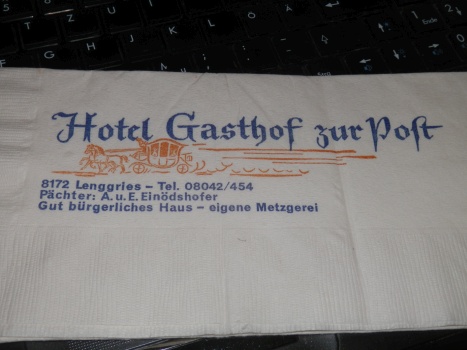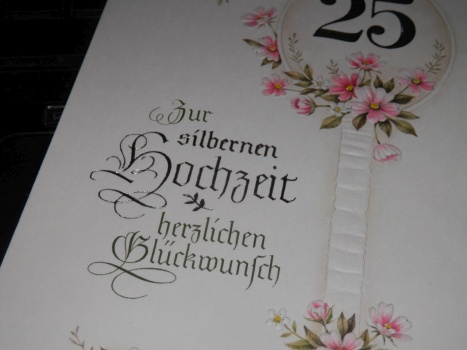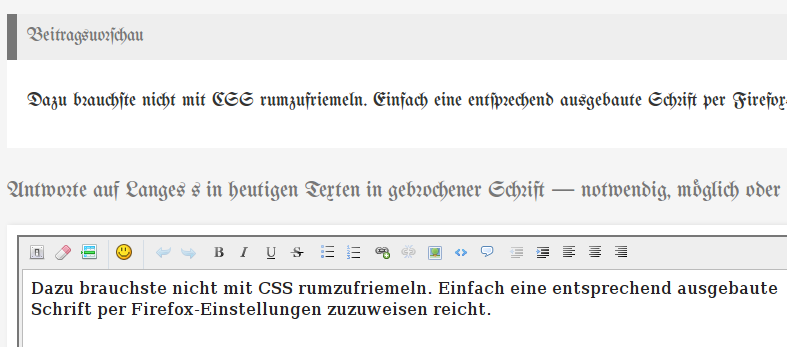
Langes s in heutigen Texten in gebrochener Schrift – notwendig, möglich oder unsinnig?
Kann vielleicht jemand ein in Fraktur gesetztes Lexikon aus dem 20. Jahrhundert empfehlen?
Wir gehen einfach direkt ins 21. Jahrhundert und schaffen eine Frakturausgabe der Wikipedia.
Beim Firefox kann man ja den Darstellungsfont selbst wählen und dabei auch einstellen, dass er Webseitenvorgaben übersteuert.
So habe ich schon Seiten in Sütterlin anzeigen lassen spaßeshalber ;-)
Wurde hier nicht mal berichtet, dass es via Opentype möglich ist, fast an allen Stellen das lange s korrekt zu setzen?
Wenn Firefox das auch nutzen kann, wäre man ja am Ziel ... ;-)
Wurde hier nicht mal berichtet, dass es via Opentype möglich ist, fast an allen Stellen das lange s korrekt zu setzen?
Wenn Firefox das auch nutzen kann, wäre man ja am Ziel ... ;-)
Siehe hier, Seite 36 in den Anleitungen.
Eher 35? Vom Fuchs lese ich aber nix ...
Aber zurück zum Streit.
Evtl. ist ja ein Kompromiss möglich?
Fundstück beim Ausmisten, irgendwann 70er waren wir in der Ecke urlauben ...
Vom Fuchs lese ich aber nix ...
Da der Fuchs OpenType unterstützt, ist die Einbindung über eine eigen CSS-Datei o. Ä. nur Formsache, wenn ich das richtig in Erinnerung habe.
Dazu brauchste nicht mit CSS rumzufriemeln. Einfach eine entsprechend ausgebaute Schrift per Firefox-Einstellungen zuzuweisen reicht.
Und da frage ich dann immer wieder zurück: Was soll das sein, »zur Schriftart gehörenden Regeln«? Warum machst du das bei keiner einzigen Antiqua-Schrift, wenn das wichtig sein soll? Eine Walbaum-Antiqua hatte im Original kein ß, aber ein ſ. Warum setzt man die Schrift heute anders und keiner beschwert sich? Warum darf ich eine Trajan-Schrift mit Umlauten, Leer- und Satzzeichen setzen? Das sind doch nicht die »zur Schrift gehörenden Regeln«!
Warum soll einer von unzähligen Schriftstilen im System der lateinischen Schrift so völlig anders behandelt werden als alle anderen?
Die Regeln gehören nicht zu den Frakturen als Schriftarten (fonts), sondern zu der Fraktur als einer Schrift (script).
Man kann Frakturen als Schriftarten (fonts) auffassen. Dann gehören sie zur selben Kategorie wie eine Helvetica oder eine Bodoni usw. – man kann einfach den Text auswählen und die Schriftart ändern. Nichts mit langem ſ oder Sperren oder sonstigen Abartigkeiten. Daran ist nichts auszusetzen.
Man kann aber die Fraktur auch als eine Schrift auffassen. Dann gehört sie in eine völlig andere Kategorie – nicht auf der gleichen Ebene wie Futura oder Bodoni usw., sondern auf der gleichen Ebene wie Antiqua und gälische Schrift. Nicht umsonst sieht der Standard ISO 15924 auch unterschiedliche Codes vor: Latn («Lateinisch»), Latf («Lateinisch - Fraktur-Variante») und Latg («Lateinisch - Gälische Variante»). Der Grund, warum es für diese Schriften (scripts) unterschiedliche Codes gibt, liegt darin, dass sie sich nicht einfach so ineinander umwandeln lassen. Es braucht zusätzliche Anpassungen. Bei der Fraktur betrifft dies etwa das lange ſ, das Sperren oder die Spezialzeichen ch, ck, ſt, ſz und tz (wovon kurioserweise das ſz als ß in die deutschländische und österreichische Antiqua-Rechtschreibung übernommen wurde). Bei der gälischen Schrift kenne ich mich weniger aus, aber da betrifft es etwa die Markierung der Lenisierung durch eine Punkt oberhalb anstatt durch ein folgendes h wie in der Antiqua.
Historisch gesehen könnte man wohl neben Antiqua, gälischer Schrift und Fraktur noch andere Varianten der lateinischen Schrift als eigene Schriften (scripts) definieren. Der Grund, warum in ISO 15924 nur diese drei definiert sind, wird darin liegen, dass nur diese drei bis in die Gegenwart eine gewisse Relevanz behalten haben (z.B. für Fachpublikum).
Und können wir bitte aufhören, hier so abwertend von so etwas wie Ahnungslosen zu sprechen? Ich wiederhole es nochmal: es ist weltweit der Standard, dass ein zeitgemäßer Text nach zeitgemäßen Regeln gesetzt und ihm beliebige Fonts ohne Speziel-Orthografie zugewiesen werden können. Das ist die Norm. Wer das so macht und/oder erwartet, ist nicht ahnungslos, sondern ein normaler Nutzer von Schrift und Sprache. Abweichende historische Satzweisen sind schlicht in aller Regel nicht relevant. Der Texter des Spiegel-Covers würde eben auch »dass« schreiben und Wörter in heutiger Bedeutung benutzen, nicht in früheren. Das ist doch selbstverständlich. Weder ist der Autor ahnungslos, wenn er sowas macht, noch biedert er sich irgendwie unnötigerweise einer vermeintlich ahnungslosen Leserschaft an. Er nutzt einfach Schrift und Sprache in üblicher Weise im Interesse (der Mehrheit) seiner Leser (→ zahlenden Kundschaft).
Ich begrüsse es sehr, dass du eine Lanze brichst für die Mehrheit, die nicht über typografische Feinheiten Bescheid weiss. Aber erlaube mir, die Gretchenfrage zu stellen. Die Mehrheit hat wohl genauso wenig Kenntnis von den typografisch Feinheiten der Antiqua wie von denjenigen der Fraktur. Die Sache verhält sich zwar ein bisschen anders, weil professionell erstellte Texte die typografischen Feinheiten der Antiqua meistens korrekt darstellen. Trotzdem sind diese Feinheiten ein elitäres Wissen, mit dem sich eine gebildete Minderheit von der Mehrheit abhebt. Beim Verfassen eines Geschäftsbriefs ist die Mehrheit auf Gedeih und Verderb der Textverarbeitungssoftware ausgeliefert. Doch selbst eine perfekt eingestellte Textverarbeitungssoftware bringt nur ein gewisse Korrekturen an. Microsoft Word kann beispielsweise keine Abstände anpassen oder keinen automatischen bis-Strich setzen oder verschlimmbessert das in der Schweiz als Tausendertrennzeichen verbreitete gerade Apostroph systematisch zu einem ‘ (left single quotation mark). Wie hältst du es mit Geschäftsbriefen? Soll man sich elitär von der Mehrheit abheben, oder soll man sich dem heute üblichen normalen Gebrauch der Mehrheit anpassen?
Ich ahne es schon: Du sagst bestimmt, dass es da gar keinen Zusammenhang gibt.
Den Rest lass ich mal unkommentiert, da eher Mutmaßungen und Wiederholungen bereits diskutierter Standpunkte.
Ich konnte es mir halt nicht verklemmen, angesichts deiner Mutmassungen meine Gegenmutmassungen festzuhalten. Wir mutmassen mit gleichem Recht.
Soll man sich elitär von der Mehrheit abheben, oder soll man sich dem heute üblichen normalen Gebrauch der Mehrheit anpassen?
Aber wenn du meinst, dass diese Lesekonditionierung generell die empfehlenswerte wäre, der sich auch alle Spiegel-Cover-Gestalter, Gasthaus-Schilder-Designer usw. anschließen sollten, dann brauchst du dafür Argumente – und die wird man wieder prüfen und bewerten können …